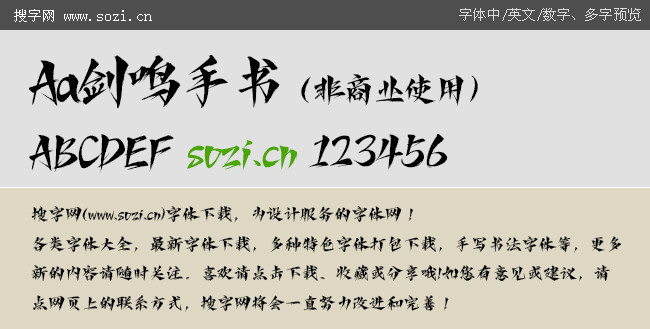
Aa劍鳴手書
搜字網(wǎng)給大家提供一款A(yù)a劍鳴手書(非商業(yè)使用)字體下載,該字體是一款手寫風(fēng)格字體,這款字體筆觸適中,書寫流暢,字形灑脫,具有很好的視覺感。適合書裝設(shè)計、包裝設(shè)計、海報設(shè)計等應(yīng)用(此字體為個人非商用版,商用可以聯(lián)系QQ:1006760504)。